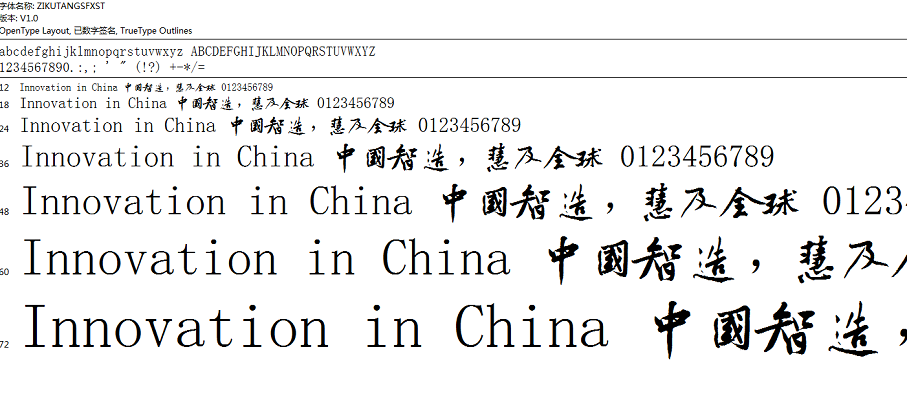
字酷堂松風(fēng)行書(shū)字體是一種行書(shū)字體,該字體清爽流暢,看似隨意卻有其獨(dú)特的風(fēng)格,給人一種流暢的美感,感興趣的朋友們快來(lái)下載吧!
字酷堂松風(fēng)行書(shū)字體是行書(shū)字體的一種,字體書(shū)寫(xiě)流暢,適用于書(shū)寫(xiě)設(shè)計(jì)字體、創(chuàng)意設(shè)計(jì)字體、藝術(shù)設(shè)計(jì)字體、平面設(shè)計(jì)字體等。
字酷堂字體制作的底稿多是采用掃描近代書(shū)法家的字帖和字跡制作而成,故書(shū)法味道挺濃(也正因?yàn)榇?,所以目前字酷堂字體多為繁體字庫(kù),簡(jiǎn)入繁出(輸入簡(jiǎn)體字直接顯示為繁體))適合用于海報(bào)設(shè)計(jì)、banner設(shè)計(jì)、包裝設(shè)計(jì)、古籍排版、網(wǎng)頁(yè)設(shè)計(jì)等方面。